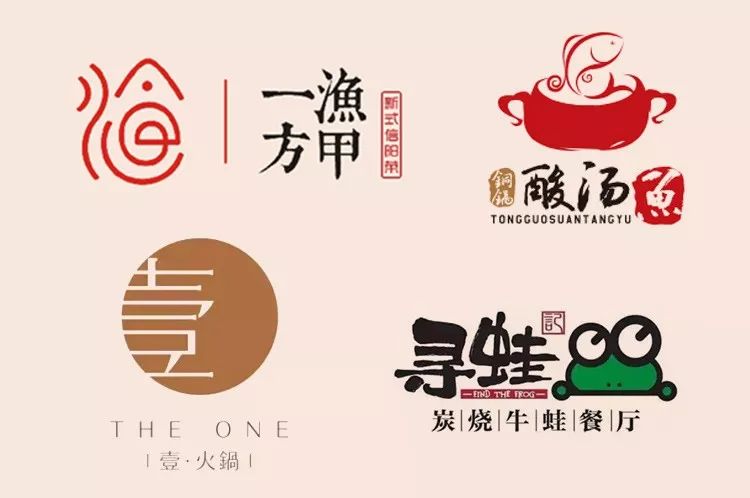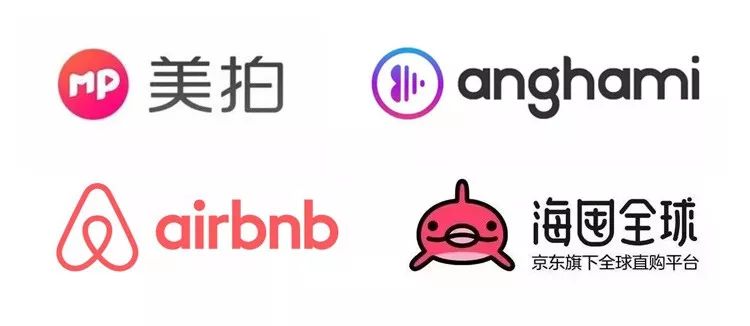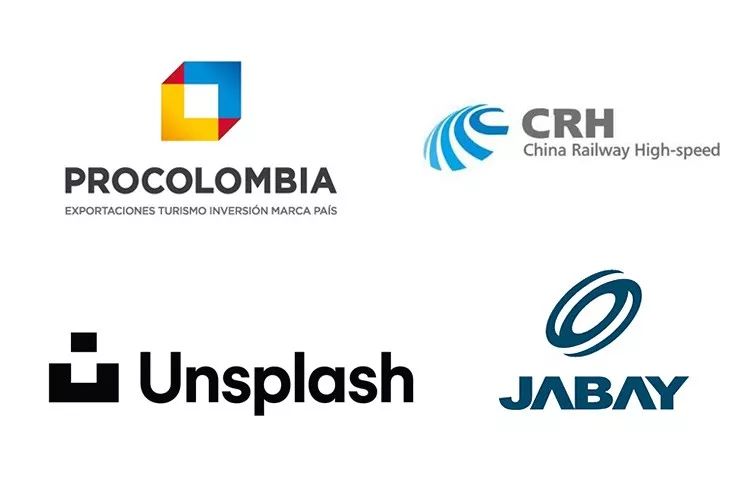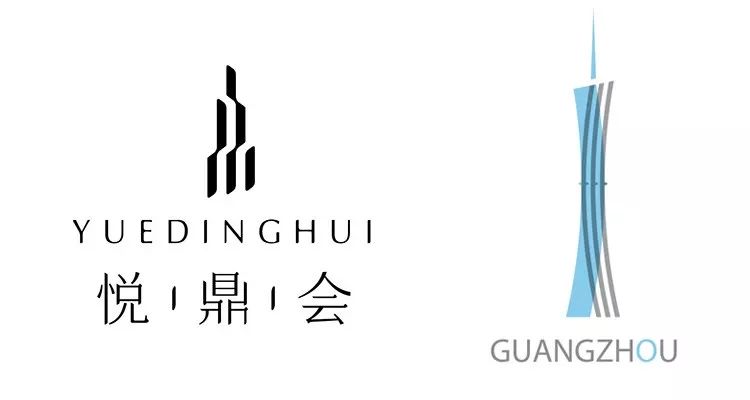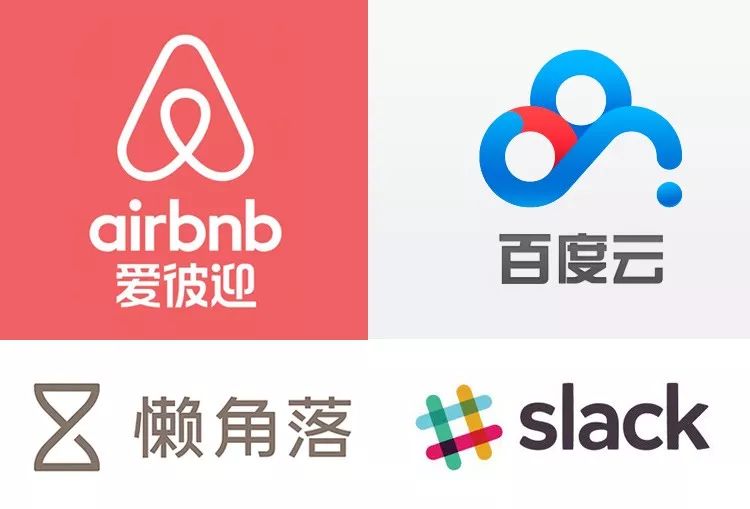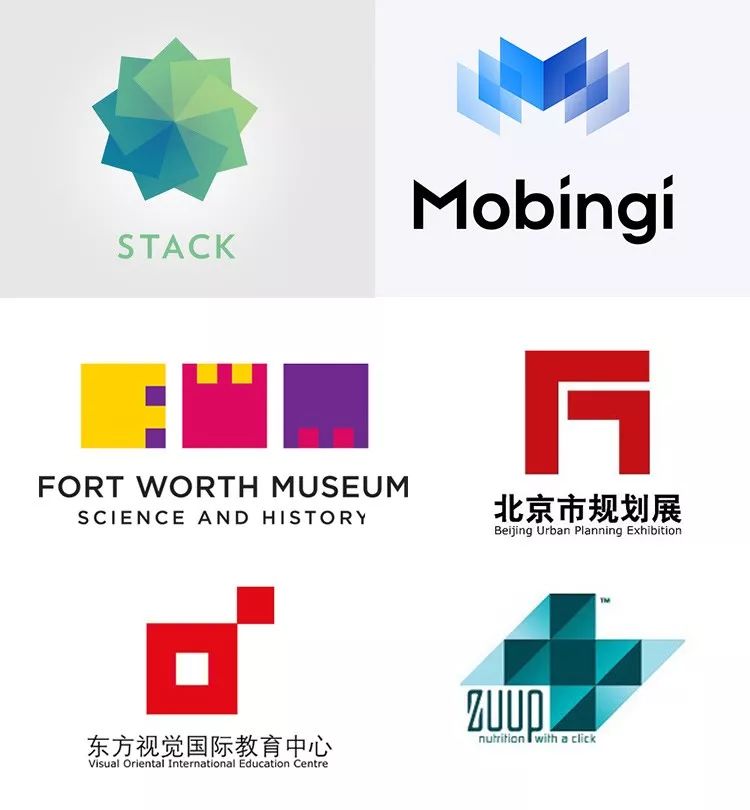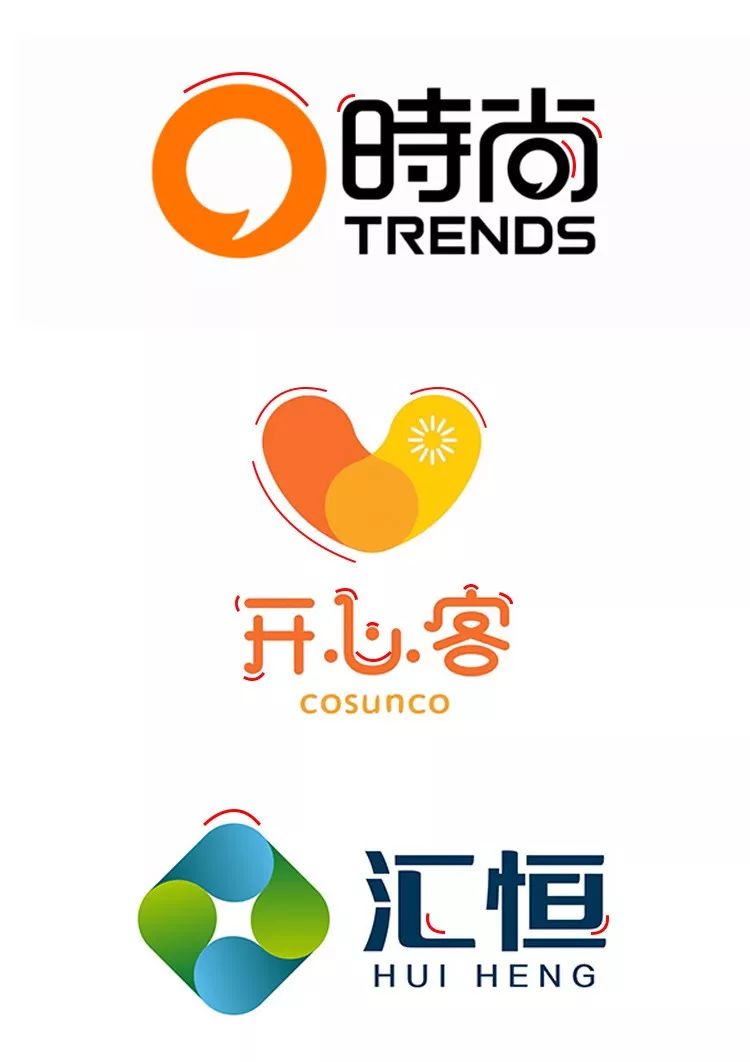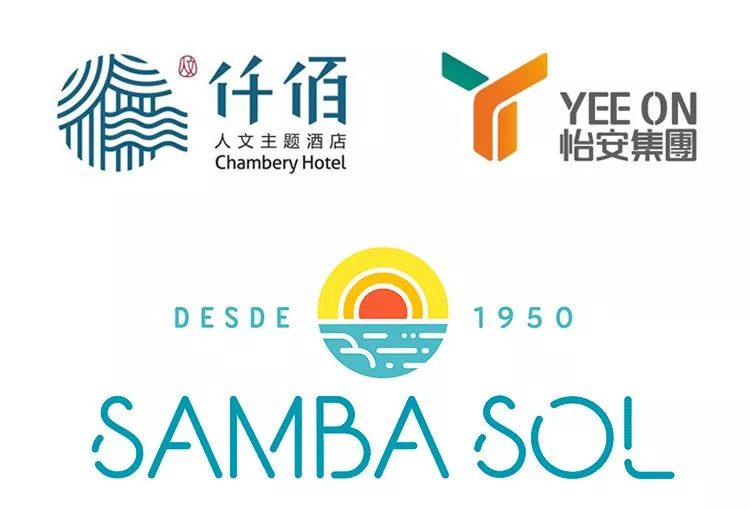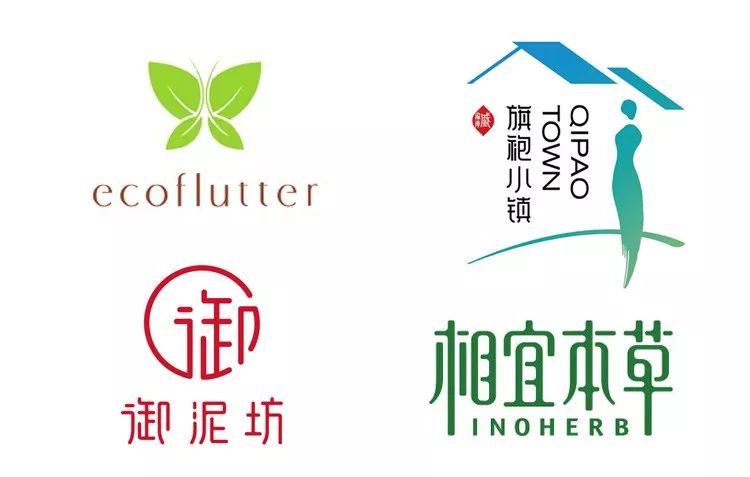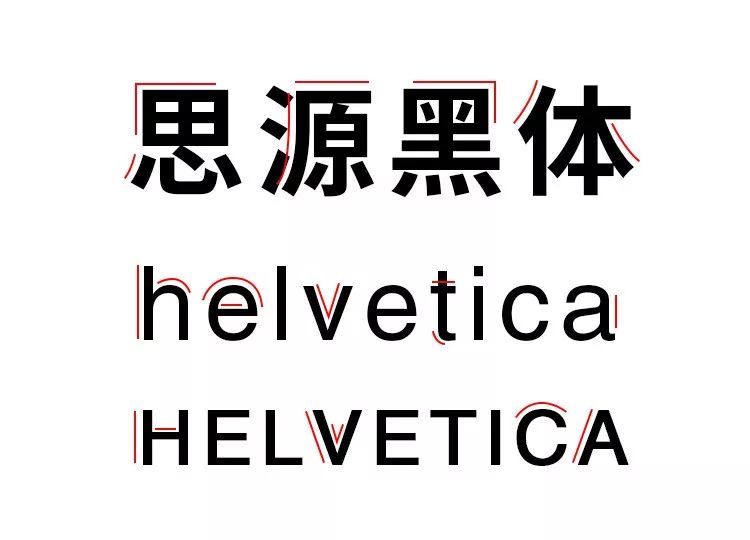
Logo图形整得很漂亮,一配上文字就糊了?
脱离了文字的图形不是一个完整的Logo,字体设计与图形设计同样重要。
虽然近年来文字型Logo和图文结合型的Logo越来越多,但图形加文字型的logo设计方向也仍然很主流,个人觉得该类Logo比前两类难度更高,因为图形加文字型Logo既要设计图形和字体,还要使logo图形与标准字非常和谐的搭在一起,事实上很多此类Logo在这方面都做得不够好。假设已经设计好了一个不错的Logo图形,那如何根据它合理地设计标准字呢?以下是葱爷的几点心得:
// 1.如何选择字体类型? //
可以作为Logo标准字的字体非常多,如黑体、宋体、楷体、隶属、行书等等,风格也很多,如优雅的、豪放的、端庄的、随意的、卡通的、文艺的等等。那么哪一种字体才是我们所需要的呢?
首先,我们得根据品牌所属的行业得出一个大概的方向。笼统的说,互联网行业和科技行业都适合把黑体(无衬线体)作为标准字。
如果Logo中有中国元素或复古元素,那么标准字可以用宋体、楷体、书法体等。
土特产和餐饮行业logo的标准字常用手写体和宋体。
有了大方向后也还不够,因为选择太多,我们得把选择范围继续缩小一点,这就需要观察图形的特征了,我们来看几个例子:
由于方圆集团的的logo图形是由一个菱形与一个圆形结合而成的,所以方圆的字体也融合这一特点,字的外轮廓用了直线与直角,在内部却做了一点圆角。
下图的蝴蝶图形线条比较随意,所以标准字也用了比较随意的手写体。
下图的logo图形为水墨风格,轮廓参差不齐,所以中文字体的笔画也保持了这一特点。
下图logo的图形部分有明显的尖角,很像罗马体的衬线,所以标准字采用了衬线体与之呼应。
// 2.采用怎样的笔画处理方式?//
如果Logo图形是只有直线没有曲线的几何图形,那么标准字的笔画是不是也应该都是尖角和直线呢?实际上这么做的案例非常少,因为这样的文字太过生硬和尖锐,很少有人希望自己的品牌给别人这样的感觉。当然,太过圆润字体以及衬线体也不行。
上面的Logo图形都是直边几何色块,但标准字的笔画都多多少少会有点弧线,如果以字库里经典的黑体字和无衬线体作为参考就会发现,上图的标准字并没有做太多改变,依然保留了原来的弧线、横平竖直、以及直角转角等特点,只不过是在细节上进一步做了简化。
如果Logo图形是曲线图形,那么标准字的笔画可以适当的增加一点圆角,如果是女性或儿童品牌,圆角可以多一点、角度可以大一点;如果是男性或科技行业的品牌,圆角则要少一点,角度也要小一点。
还有些标准字的设计会把某些笔画刻意断开,使其更有设计感和特点,一般是因为Logo图形中也有类似的效果。
// 3.采用怎样的笔画粗细? //
笔画的粗细也是由品牌的行业属性以及图形决定的,如果是重工业、建筑业的Logo,那么标准字的笔画应该粗一点.
而如果是护肤品、化妆品、服装、健康行业的品牌,那么字体的笔画可以相对细一些。
此外,字体的笔画粗细也要以图形为设计依据,如果Logo图形是等线型的,那么标准字通常也会用等线体,至于笔画的粗细通常也要呼应图形。
你们应该也有发现,很多Logo的标准字融合了宋体与黑体的笔画特点,即去掉了宋体衬线,但保留了宋体横细竖粗的效果,这种字体比宋体更现代、更简洁,比黑体又多了一点变化和优雅。而横竖笔画的比例大小也会影响字体的效果和气质,相差大的会比较精致,相差小的会比较现代、易落地。
// 4.如何设定文字高宽比? //
除了字体的类型、风格、笔画以外,字体的宽高比也与图形有莫大关系,如果图形的轮廓倾向于一个正方形或者正圆,那么文字(中文)的高宽比通常也会接近1:1。
如果图形是比较高瘦的,那么文字就不能太矮胖,不过,为了保持平衡,也不要把文字拉得太瘦长。
同样,如果图形是比较扁的,文字就不能太纤瘦。
设计师都知道设计中几乎不存在什么一成不变的方法,所以上面的观点仅代表一种比较大众的现象,可以保证不会做错但不是唯一的标准,也不一定是最好的选择,如何把握需要我们在实践中慢慢去摸索。不过在给logo图形配文字的时候有几个原则还是要坚持的,即必须与品牌调性相符、必须与图形搭配和谐、且不能设计得太过花哨。